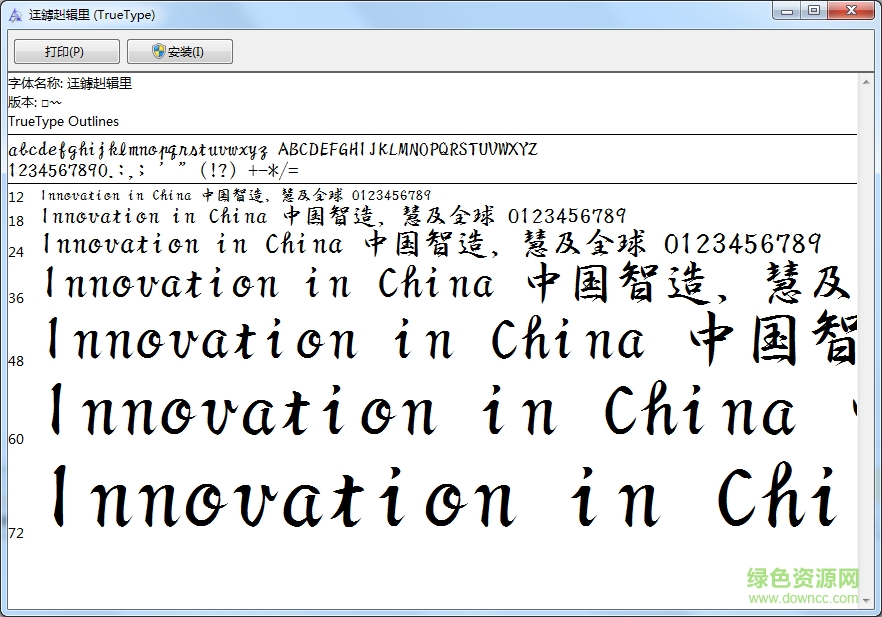
祥南行書(shū)體是一款非常大氣的字體,字體優(yōu)雅自然,字形呈發(fā)散狀,非常的漂亮,適用于廣告設(shè)計(jì)和商業(yè)使用,歡迎大家到綠色資源網(wǎng)下載使用!
該字體字形端正、整齊美觀、大氣自然,整體效果十分出色,用戶輸入繁體字才能夠見(jiàn)到該字體的效果,可以應(yīng)用于藝術(shù)設(shè)計(jì)、包裝印刷、廣告設(shè)計(jì)、平面設(shè)計(jì)等領(lǐng)域